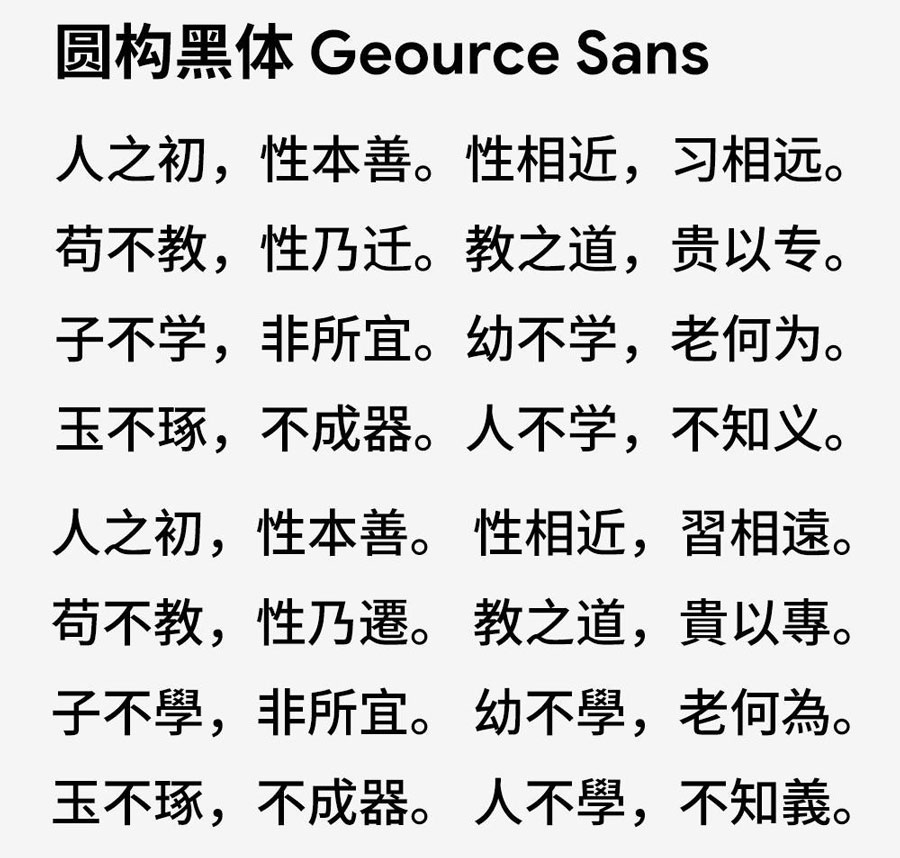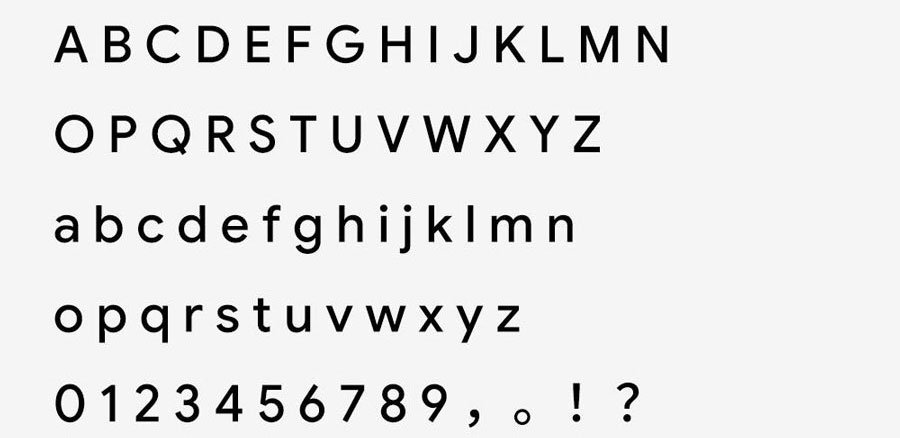
圆构黑体支持包括汉字、假名、谚文、拉丁文、希腊文、西里尔文等在内的多种文字系统,提供中国内地字形(CHS)、昭源现代笔形(CHT)、日本字形(JPN)等三个版本,还有另外的”圆构黑体 Alt “版则是采用等宽数字、全角引号和单层“a”字形,优化了特定场景下的显示效果,以满足不同地区不同场景下的审美和使用习惯。